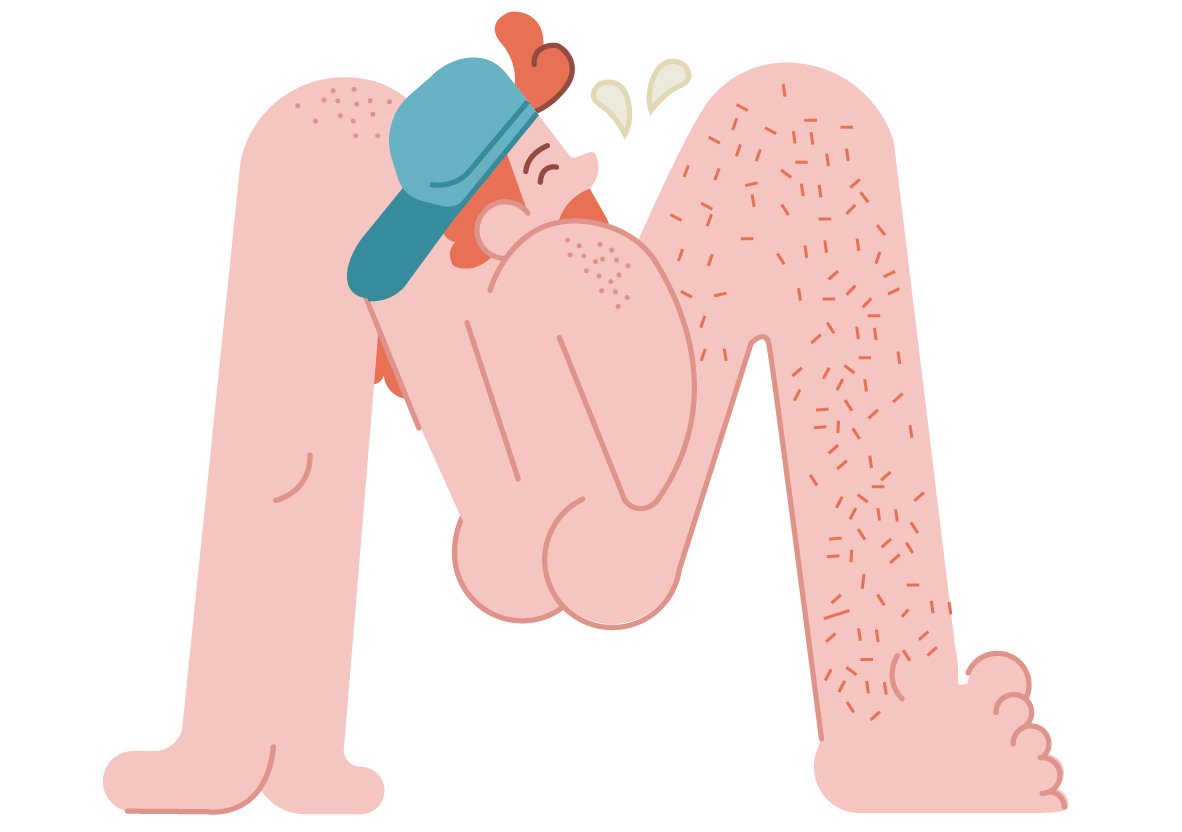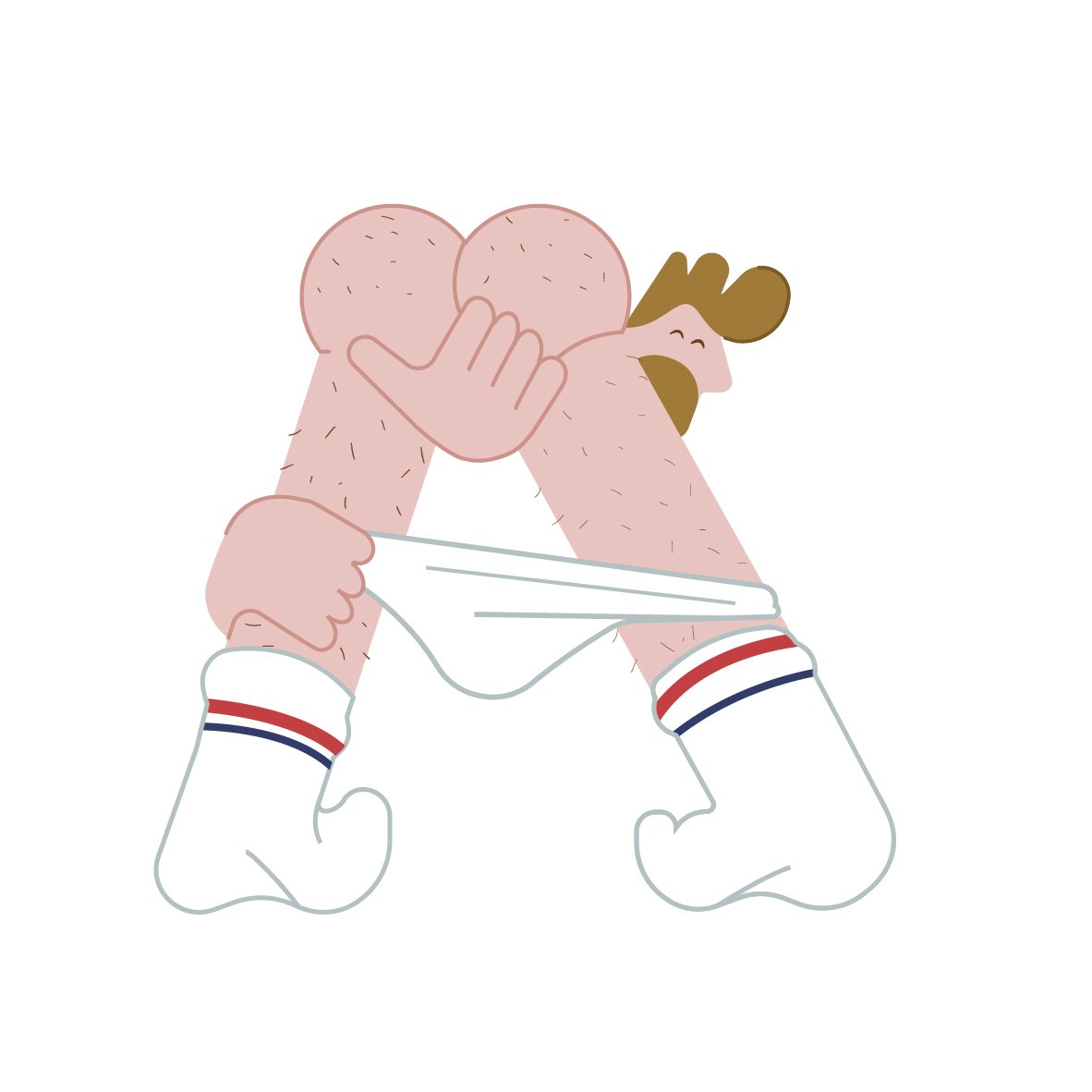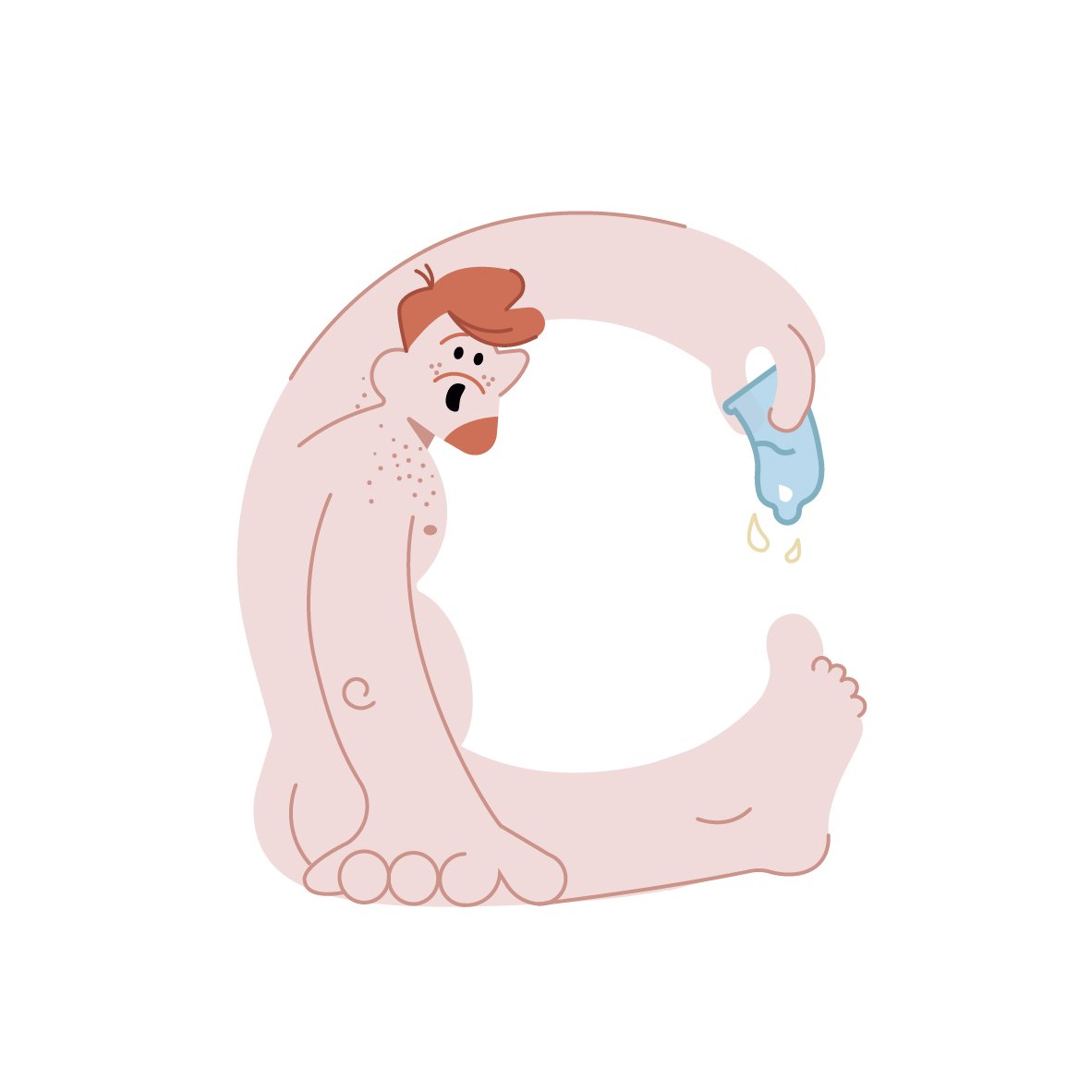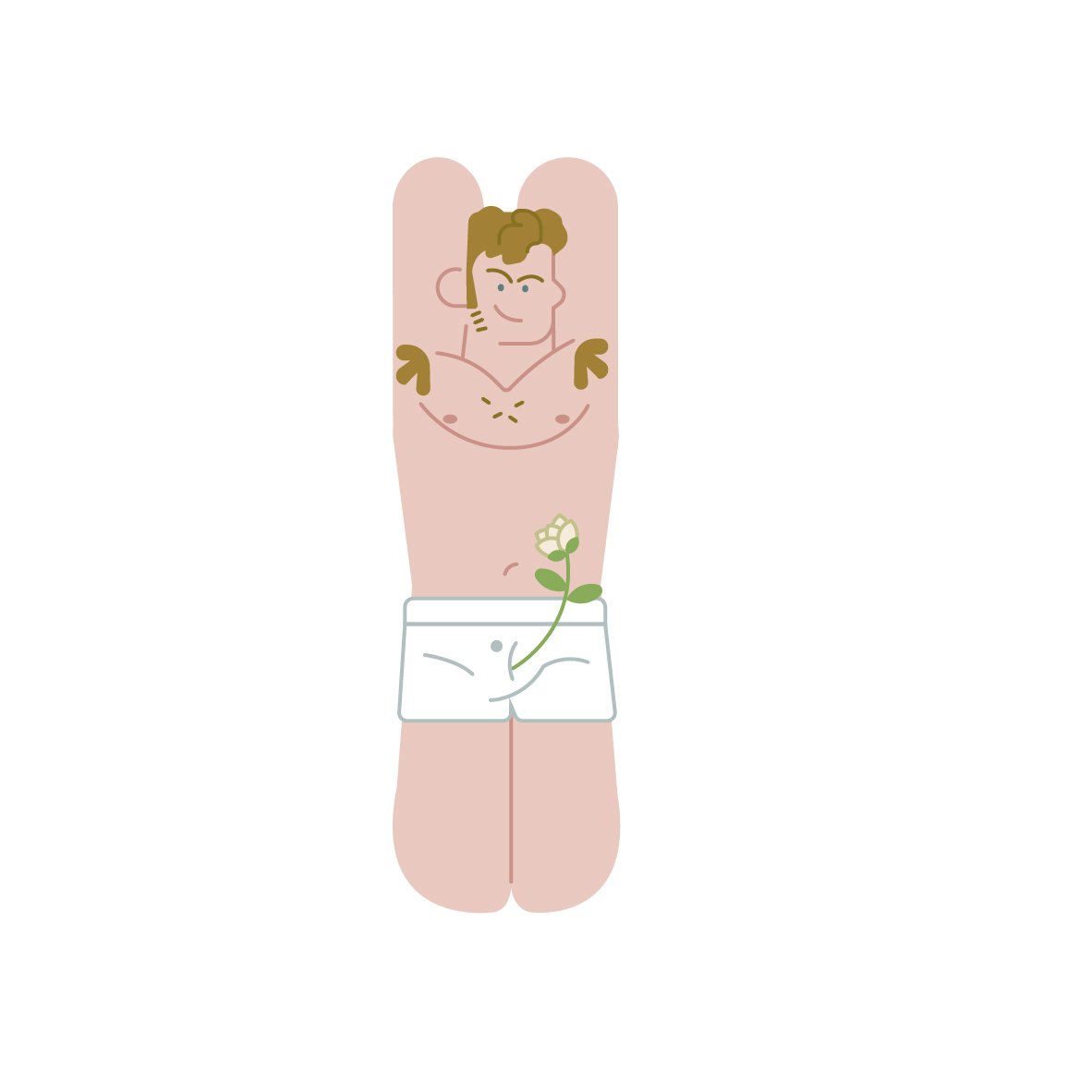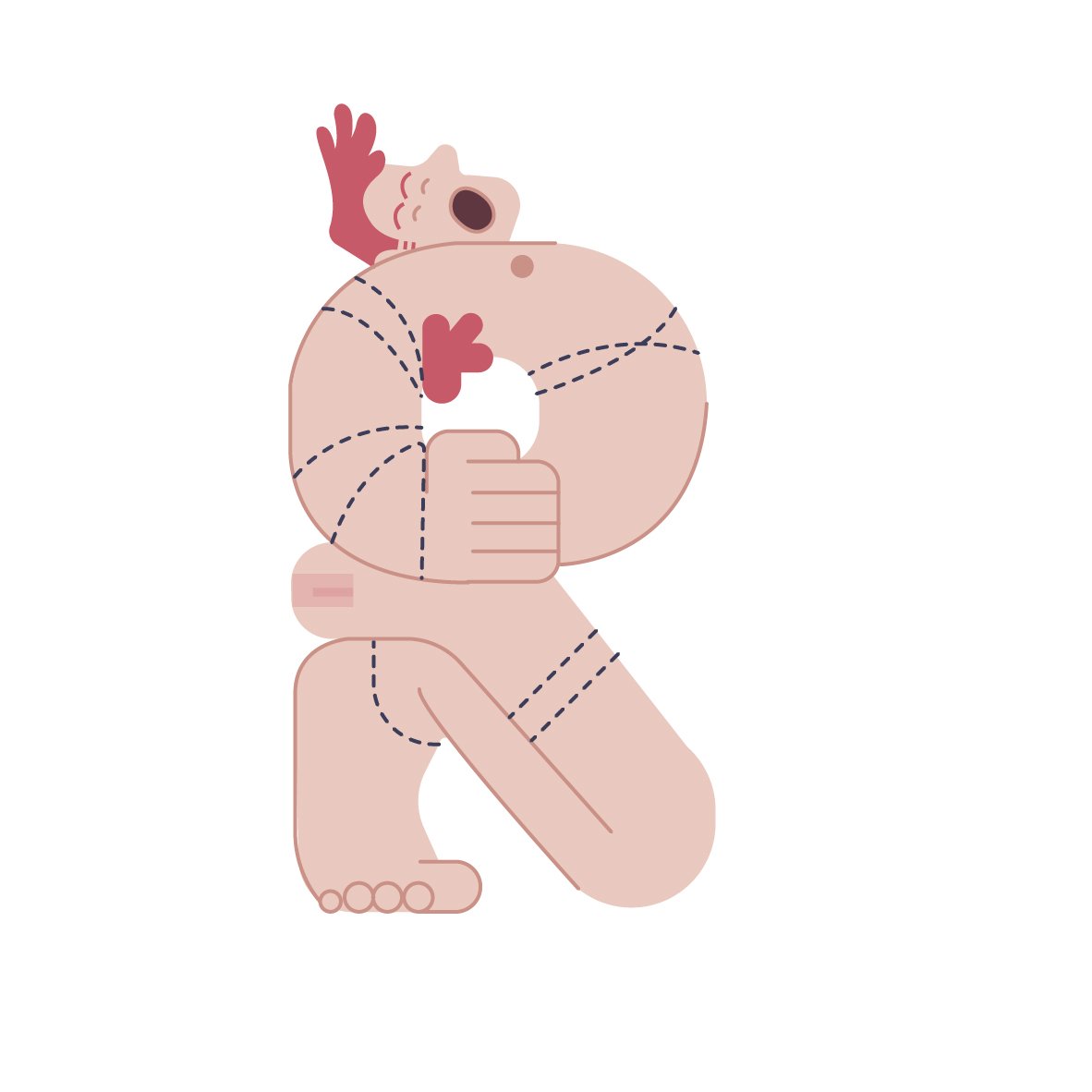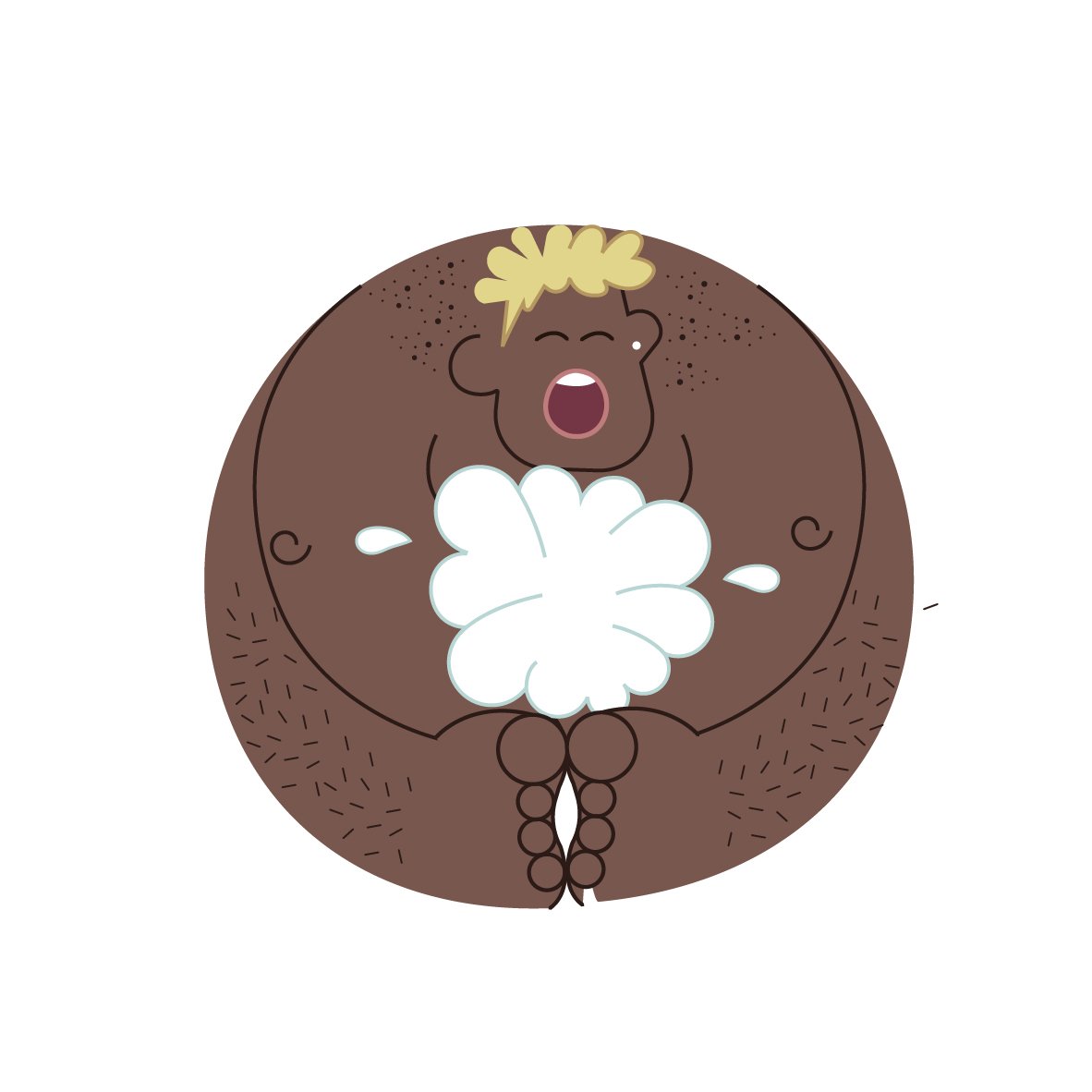
M-A-R-I-C-Ó-N. Cuando pedimos a Jaime Hayde que componga una palabra con su tipografía gay se lo piensa un poco antes de apostar por esta. «Es que la he odiado durante muchos años, pero hemos sido capaces de darle la vuelta y ahora me gusta cuando la escucho en boca de gente en tono cariñoso, divertido, romántico e, incluso, lujurioso».
Tiene Hayde un abecedario entero con el que componer las palabras que quiera. Todas las letras tienen la forma de hombretones apuestos en actitud sexual y todas hacen referencia a un término erótico. La a es de anal, la d de dildo, la e de erección…
La idea de crear una tipografía gay le surgió a este ilustrador por casualidad. Vio en televisión una noticia sobre las terapias de conversión y se le encendió no tanto una bombilla como un fuego dentro. Pero Hayde decidió convertir aquel cabreo en creatividad y se puso a hacer lo que mejor sabe: dibujar. «Justo empezaba el 36 days of type [convocatoria abierta que propone a diseñadores reinterpretar el abecedario durante 36 días] y me lancé».
Letra a letra, el trabajo de Hayde fue pasando del cabreo al jolgorio sexual, hasta acabar componiendo un abecedario a medio camino entre lo lujurioso y lo reivindicativo. Como casi todo su trabajo personal.
Jaime Hayde tiene una relación terapéutica con la ilustración. «Dibujar me ha servido para aceptar muchas cosas», explica. La primera fue quizá su sexualidad. «Provengo de un entorno católico y los dibujos me ayudaban a aceptarme a mí mismo y a mostrarme, sobre todo con mis hermanos pequeños», reflexiona.
La segunda fue el trauma de crecer como persona racializada en un entorno monolíticamente blanco. «Desde pequeño he tenido pocos referentes multirraciales fuera de mi núcleo familiar».
Como no había referentes de carne y hueso, Hayde decidió dibujarlos. De esta forma, explica, «con el tiempo, muchas cosas que tenía interiorizadas han ido saliendo». En el caso de la tipografía gay, los dibujos le han servido para aceptar ciertas partes de su cuerpo de las que estaba acomplejado y que ha puesto en primer plano.
Aunque el resultado tiene una alta carga personal, reconoce Hayde que el proceso de creación ha tenido algo de colectivo: «Cada día pedía por Instagram ideas a la gente para la siguiente letra, era un proceso que me encantaba».
Parte del mismo se puede rastrear en su feed de Instagram, en un ejercicio curioso en el que se aprecia cómo el autor toma y adapta ideas de forma ciertamente inteligente. «No quería ser demasiado explícito», comenta, aunque al final ha tenido algún problema de censura en plataformas como Behance.
También ha tenido otros problemas a los que empieza a estar acostumbrado. «En más de un proyecto he recibido comentarios negativos por incluir personajes de diferentes razas», explica resignado. «Incluso en el mundo gay hay mucha discriminación y es algo que me cuesta entender, hay discriminación contra la gente de otras razas, contra la gente con pluma, contra los gordos… la lista es bastante larga».
Muchos de estos prejuicios están interiorizados y se perpetúan de forma inconsciente. El propio Hayde se encontró uno de ellos hace poco escondido entre sus dibujos. «Hace unos meses unos amigos estaban viendo mi cuaderno de dibujo e hicieron el chiste sobre que había mucho músculo y me dije ‘pues tienen razón’. Muchas veces dibujo algo porque me parece bello, pero desde ese momento intento buscar referencias más diversas para mis dibujos».
Jaime Hayde estuvo a punto de ser otro Jaime Hayde. En un principio dudó sobre si debía o no postear dibujos de temática gay. «Al final llegué a la conclusión de que este soy yo, y a quien no le gusten mis dibujos por su contenido probablemente tampoco le guste yo», resume.
Desde que tomó esa decisión, Hayde ha ido conjugando activismo e ilustración, diseño y reivindicación LGTBI+. Ambos extremos, asegura, casan perfectamente: «Solo hay que ver muchas de las campañas del Ayuntamiento de Madrid de los últimos años».
También destaca el trabajo de diseñadores como Alfredo Roagui, The Cute Brute, Johann Andreu, Luc Latulippe, Dronio, Hey Rooney… «La historia del diseño gráfico está plagada de ejemplos». Y más que va a haber. Hayde es consciente de que queda mucho por reivindicar. Él quiere aportar su granito de arena a su manera: dibujando un mundo mejor.